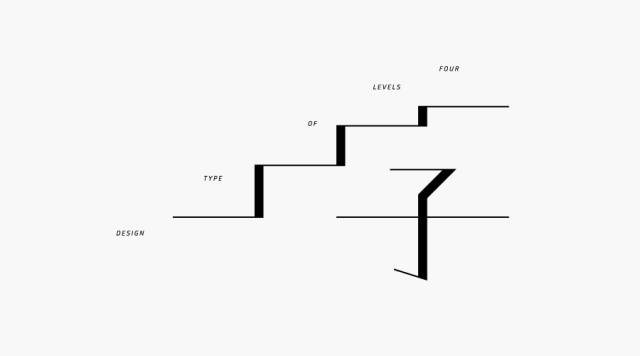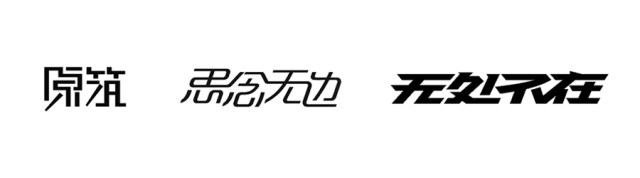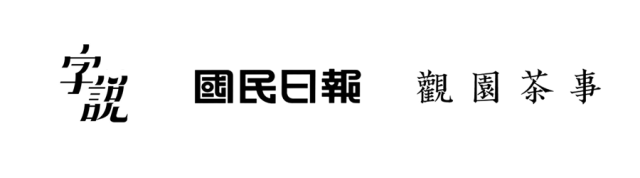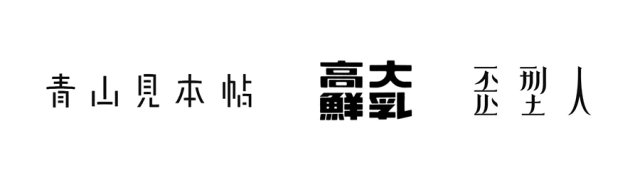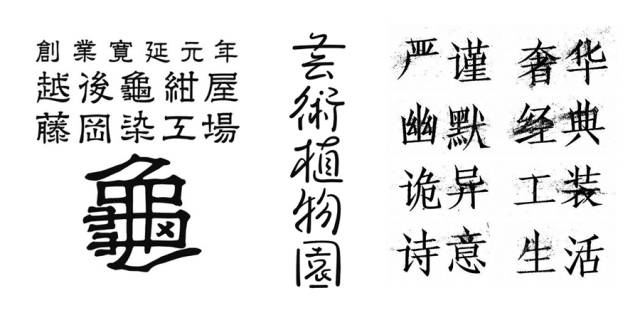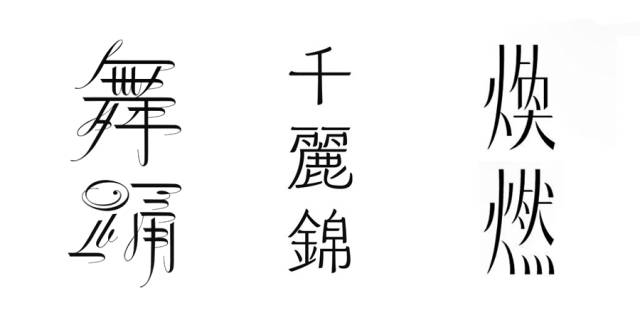
字型设计的四个层次:变化、规矩、破除、立规
按:几天前,在学习视频课程《治字百方》的同学群里讨论字型,说了一段关于字型设计的几个层次的话,很多同学有感触。记录在这里分享给更多人。并非每个人都需要到达顶端,但有你必须到达的基本层次。混生活的、当工作的、凭兴趣的、天赋异禀的……都需要到哪个层次,却是有说法。
1 . 变 化
变化很多,形式各样。大部分把字当作图形,大胆拆分。因大部分人并不真正知道字如何写,有什么规矩,只要能认识,任何手法都是可以用在字型上。
其实按目前的审美大环境来看,一般的海报、banner、包装名、广告slogan等,会变化就足够了。换句话说,如果没甚追求,只是当个混饭吃的工作,到此就足够了。
2 . 规 矩
第一阶段后,对字有真正兴趣,或者对单纯玩形式感到索然的人,会进一步了解它的一切,比如工具笔墨纸、历史、故事、其他文字、以至自己书写,这就进去了第二阶段。相比之前的无畏外放,会知道收一些,会了解很多规矩,这时虽然比之前知道的多很多,但自己反而因为字的水深而觉得无知,做字的时候也不会再肆意乱改,会有些规矩去遵循,时间久了反而会有种被规矩所累的无力感。大部分人止步于此。
对于“合格的专业设计师”这个称呼来说,止步于此是必要的要求;换个说法,止步于此,也可以担起“合格的专业设计师”这个称呼。
3 . 破 除
这时如果兴趣不减,或者天赋异禀,会根据自己的理解破除束缚自己的规矩。这时会发现,变化又多了起来,只是看上去更耐人寻味,更不容易被人模仿,也可以说有规矩而又破规矩的变化,就来到了第三阶段。
常说“大部分人在模仿,只有很少一部分人在创造。”这很少一部分人就是来到这个阶段的人。他们是我们经常说的“翻看网站,找找灵感”的“灵感缔造者”。
4 . 立 规
这一阶段,你自己的作品就是别人的规矩了。这时会把上一阶段的散沙式的“灵感”,用逻辑理论串联起来,形成风格、系统、主义。也就是那些在设计简史中有一笔记录的大师。
胡适说过一句话:“创造是一个最误人的名词,其实创造只是模仿到十足时的一点点新花样。”既说明了这四个阶段的训练过程,也说出了每个阶段的状态。开始的“模仿”,到“模仿到十足”,再到“一点点新花样”,这一点新花样说起来何其简单,但就是这一点新花样在推动设计不断向前。